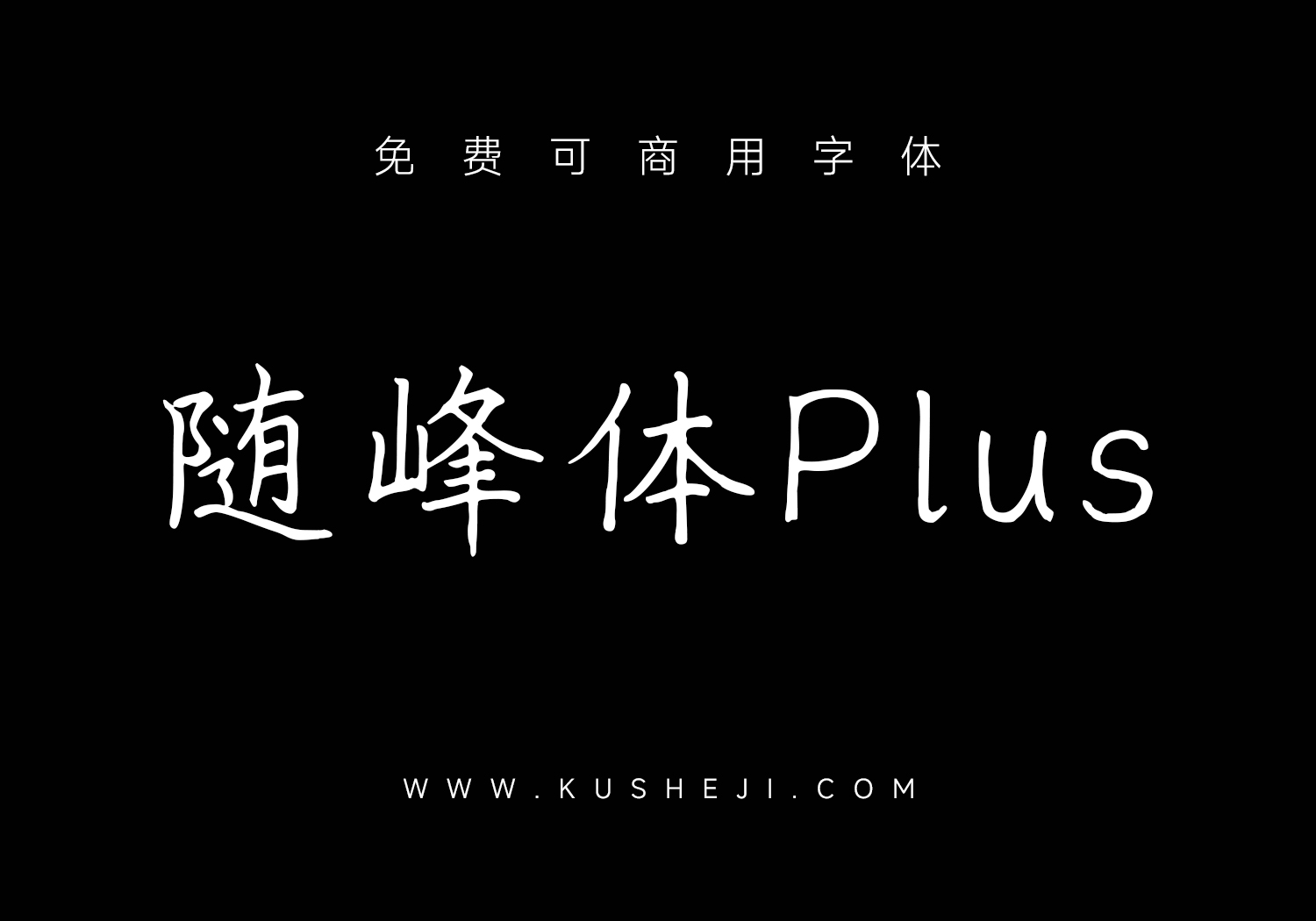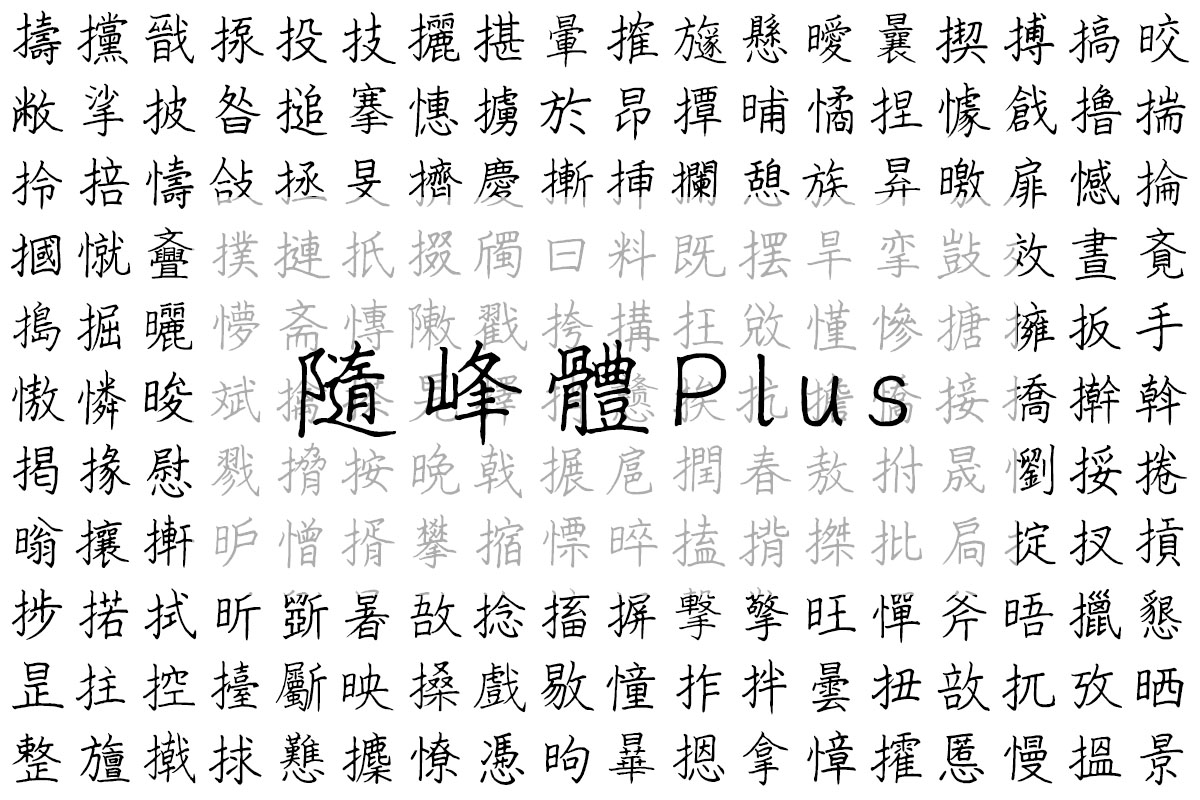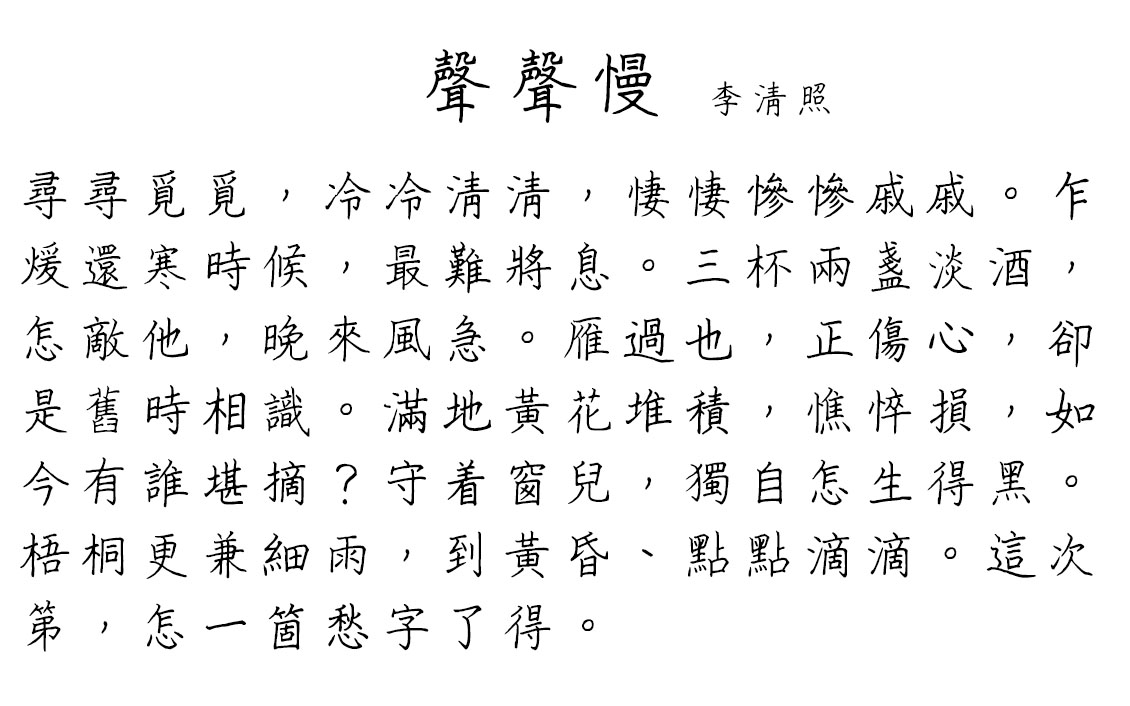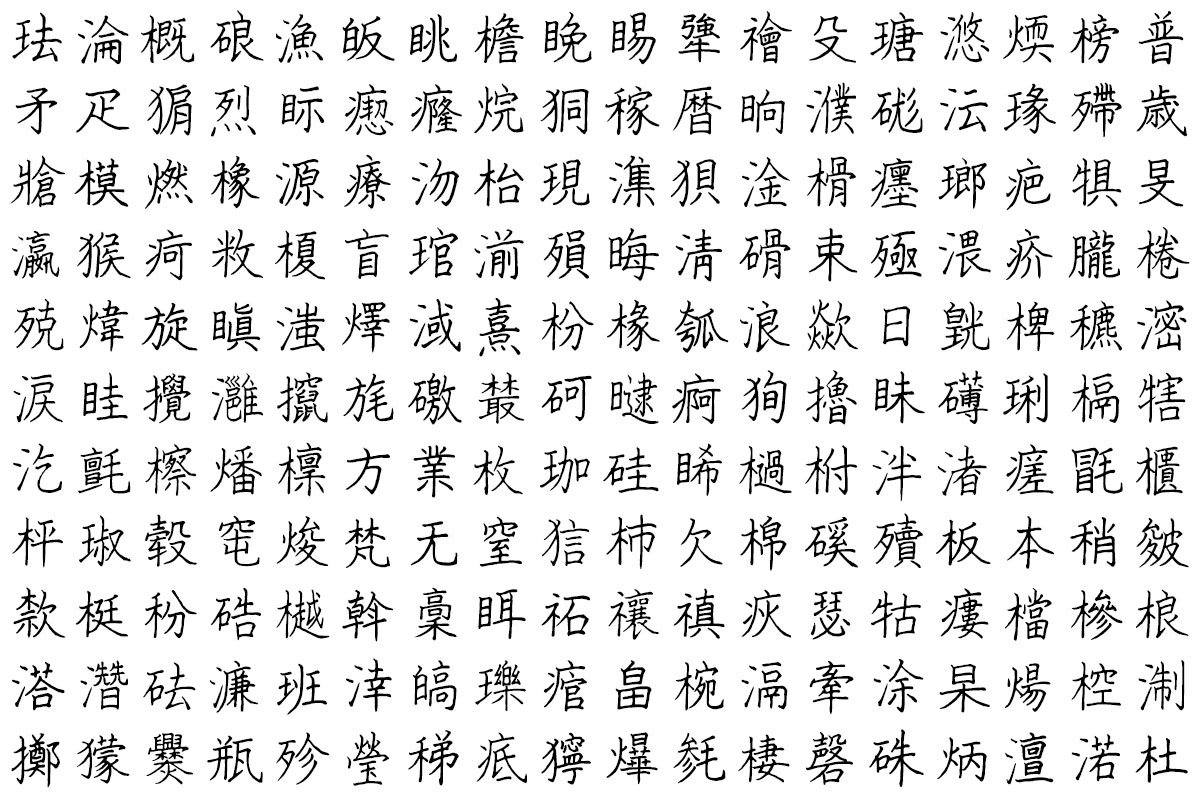
随峰体是创作者阿坤的手写作品,是 cjkFonts 在2022年公开的开源字形,不但免费,更可供个人及商业使用。
随峰体自推出后大受欢迎,不但应用很广,还有多个衍生创作版本。当中最大型的,有晓声通秋茄体,增补了《国语辞典》(包括《简编本》、《重编本》、《成语本》)中所有用字,补充至逾15000字。同时亦有其他补充和修改“随峰体”字形的版本。
爲方便“随峰体”的使用者,我们 cjkFonts 的字型设计师以“随峰体”原档案爲基础,整合不同的衍生版本,并再添补和修订使用者有需求的字,把新制作成果发佈作“随峰体Plus”。除了原来的“随峰体”外,“随峰体Plus”也以开源字型一併发佈,免费提供及每位使用者作各种个人及商业使用。
字数大约16400(包括数字、英文、标点符号)。